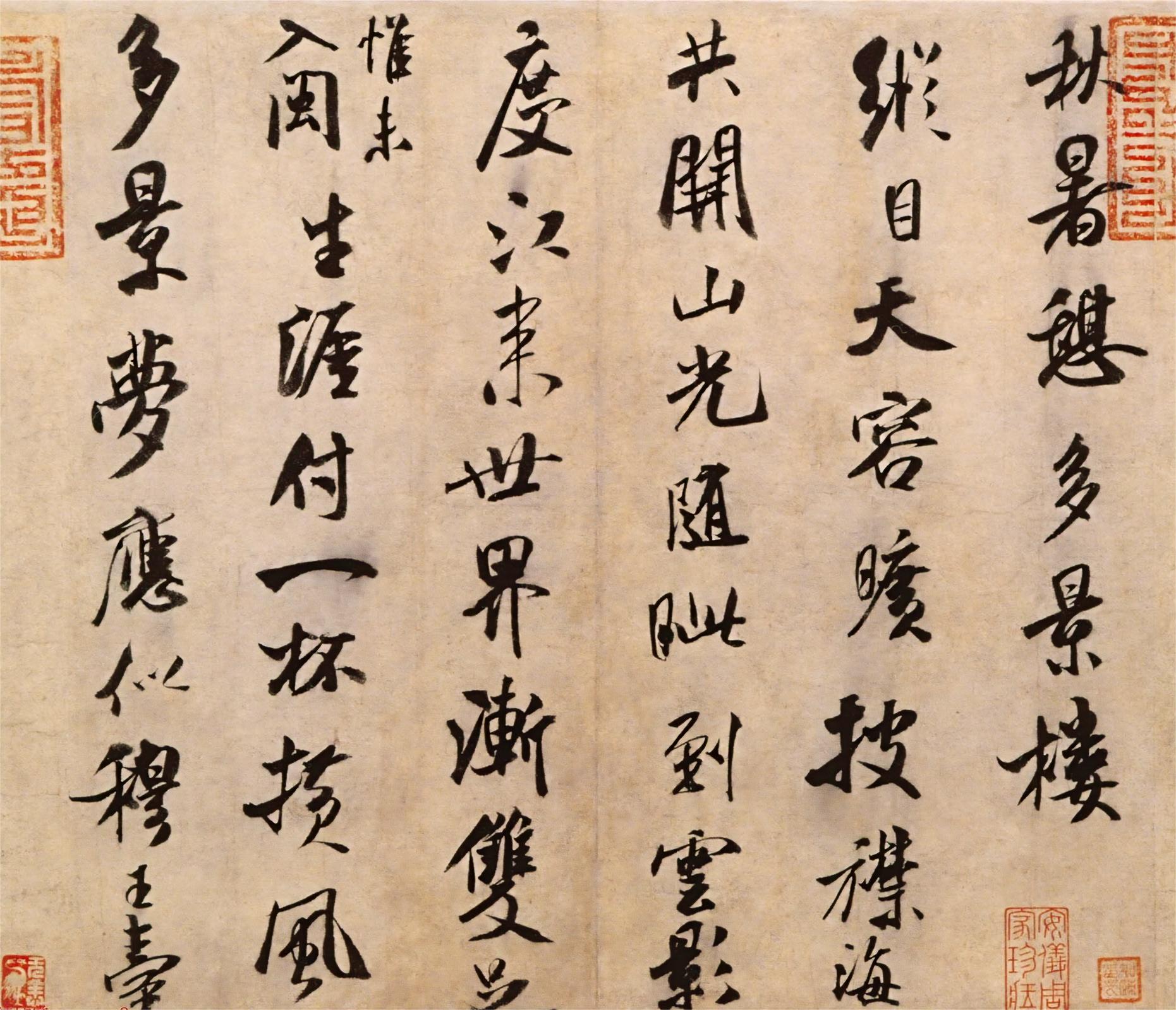
字体全名: 汉标米芾秋暑憩多景楼帖
字体简介: 下载须知:本字库非标准GB2312字库。本字库只包含了米芾《秋暑憩多景楼帖》真迹上的“60个字”。米芾行书欣赏《秋暑憩多景楼帖》纸本,米南宫书于元佑元年(1086年),纵27.6厘米,横34.3厘米,北京故宫博物院藏。米芾的书法在宋四家中,列苏东坡和黄庭坚之后,蔡襄之前。然如果不论苏东坡一代文宗的地位和黄庭坚作为江西诗派的领袖的影响,但就书法一门艺术而言,米芾传统功力最为深厚,尤其是行书,实出二者之右。明代董其昌《画禅室随笔》谓:“吾尝评米字,以为宋朝第一,毕竟出于东坡之上。即米颠书自率更得之,晚年一变,有冰寒于水之奇。”